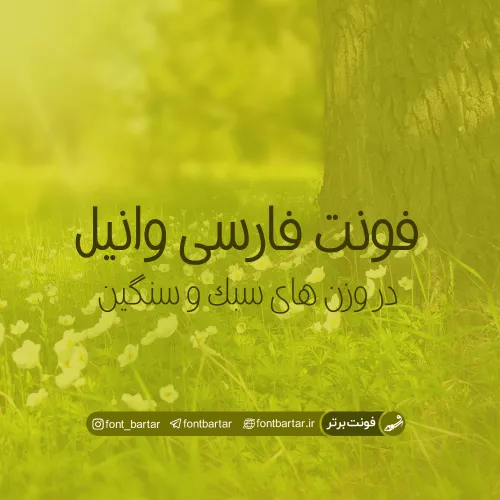
فونت فارسی وانیل
دانلود فونت فارسی وانیل Mj Vanilla تایپ عربی و فارسی با کیفیت بالا و فرمت ttf مناسب برای استفاده در کارهای گرافیکی و تبلیغاتی که در وبسایت فونت برتر برای شما کاربران عزیز آماده دانلود شده است.
فونت وانیل مورد استفاده برای:
• طراحان وب سایت و گرافیست های خلاق می توانند از این مجموعه زیبا فونت در طراحی پروژه های تبلیغاتی و تجاری خود کمک بگیرند.